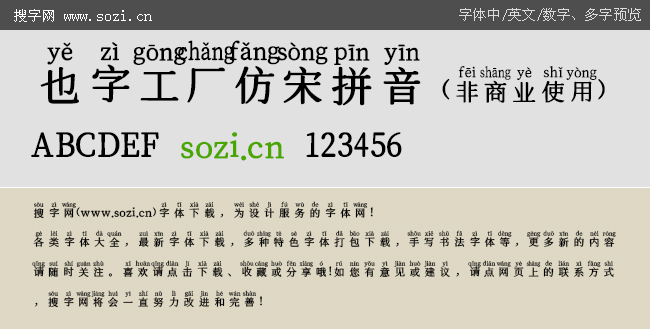
也字工廠仿宋拼音
搜字網(wǎng)給大家提供一款也字工廠仿宋拼音體(非商業(yè)使用)中文字體下載,也字工廠仿宋拼音體是一款宋體字體,字體上配有漢語拼音。適合應(yīng)用于兒童圖書、繪本畫冊(cè)、兒童海報(bào)設(shè)計(jì)等應(yīng)用(此字體為個(gè)人非商用版,商用可以聯(lián)系:官方網(wǎng)址:https://yefont.com/home,聯(lián)系方式:13798980448)。